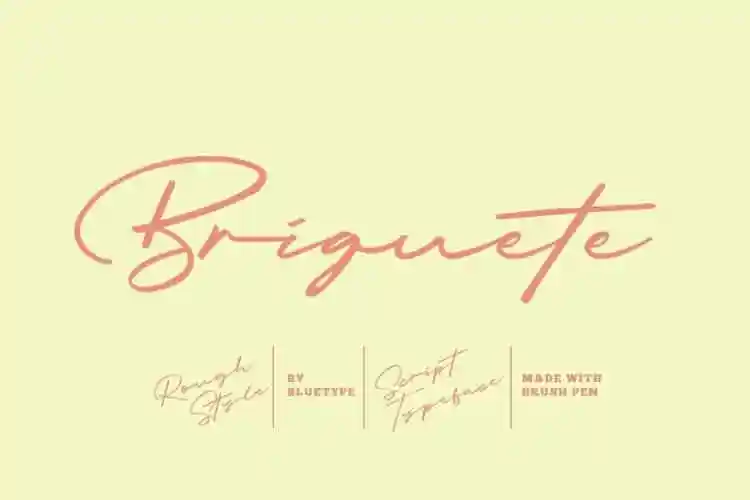
Briquete Script Font é uma elegante fonte a mão escrita inspirada no tipo de caligrafia natural com traços feitos com uma ferramenta de tinta seca e agitada, criando um design fresco e sofisticado. Desenvolvida pelo designer Hamilton e produzida pela Bluetype, esta fonte é extremamente versátil e consegue se adaptar a muitos projetos. Ela abrange várias linguagens e suporta os recursos OpenType, incluindo numerais e sinais de pontuação. Com sua qualidade natural e realista obtida através da ferramenta de tinta, ela é perfeitamente adequada para diversos tipos de trabalhos gráficos, como identidade de marca, design de casamento, publicidade, embalagens de produtos, designs de produto, etiquetas, fotografia, convites, citações e muito mais. Este tipo de fonte traz vida e originalidade aos seus projetos, tornando-o um recurso indispensável para designers que buscam adicionar um toque único a seus trabalhos gráficos.